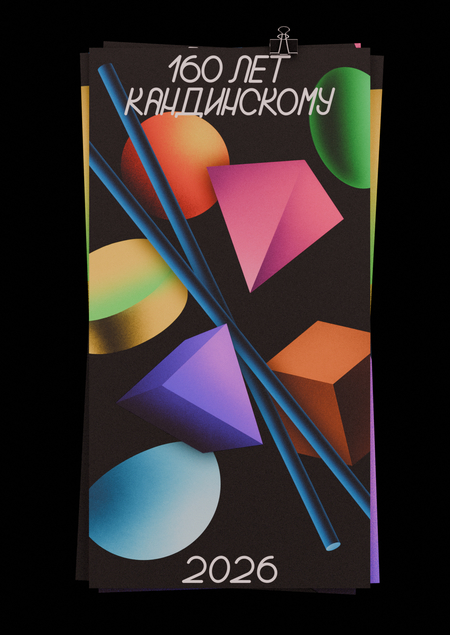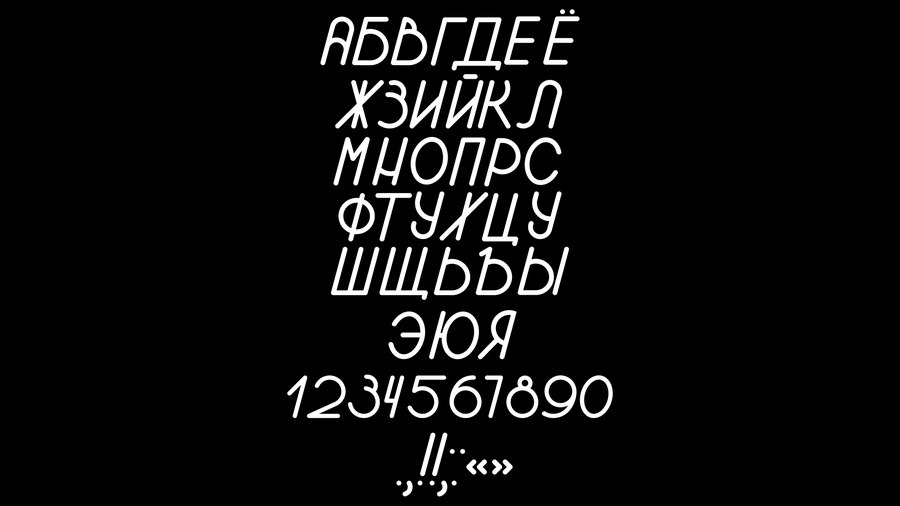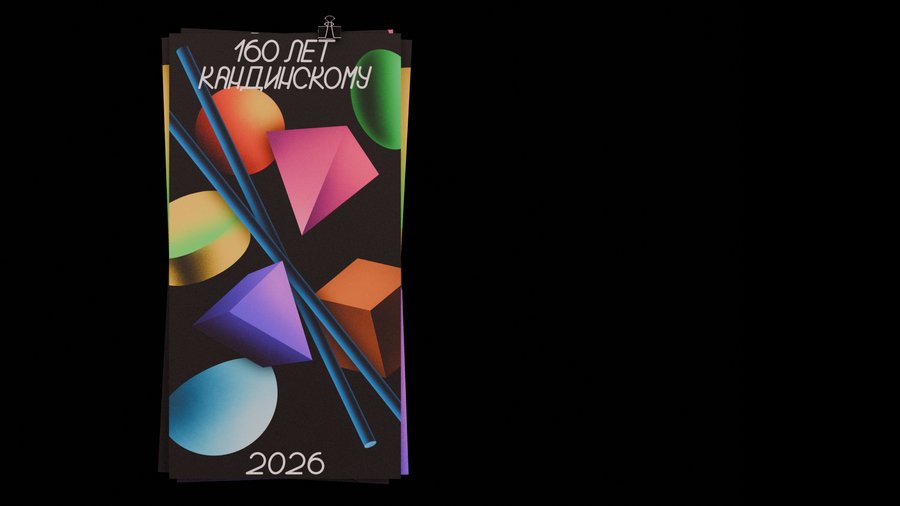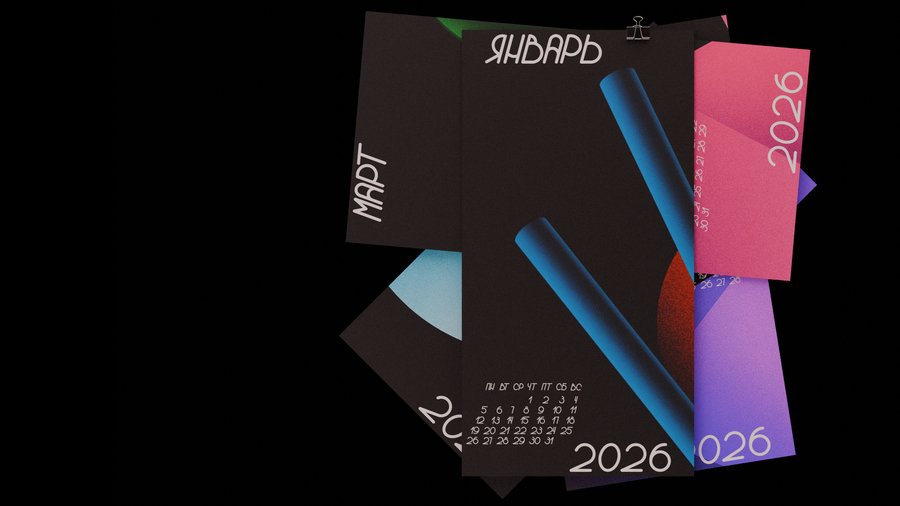
Авторский шрифт «Перспектива» и календарь к 160-летию Кандинского
В начале модуля я приступил к правкам в свой шрифт, но по итогу сделал новую кассу
Для демонстрации шрифта я решил создать календарь, выбор темы которого пал на Кандинского, а точнее на дуалистичность геометрии в его творчестве: порядок и хаос, бессистемность и стремление к балансу